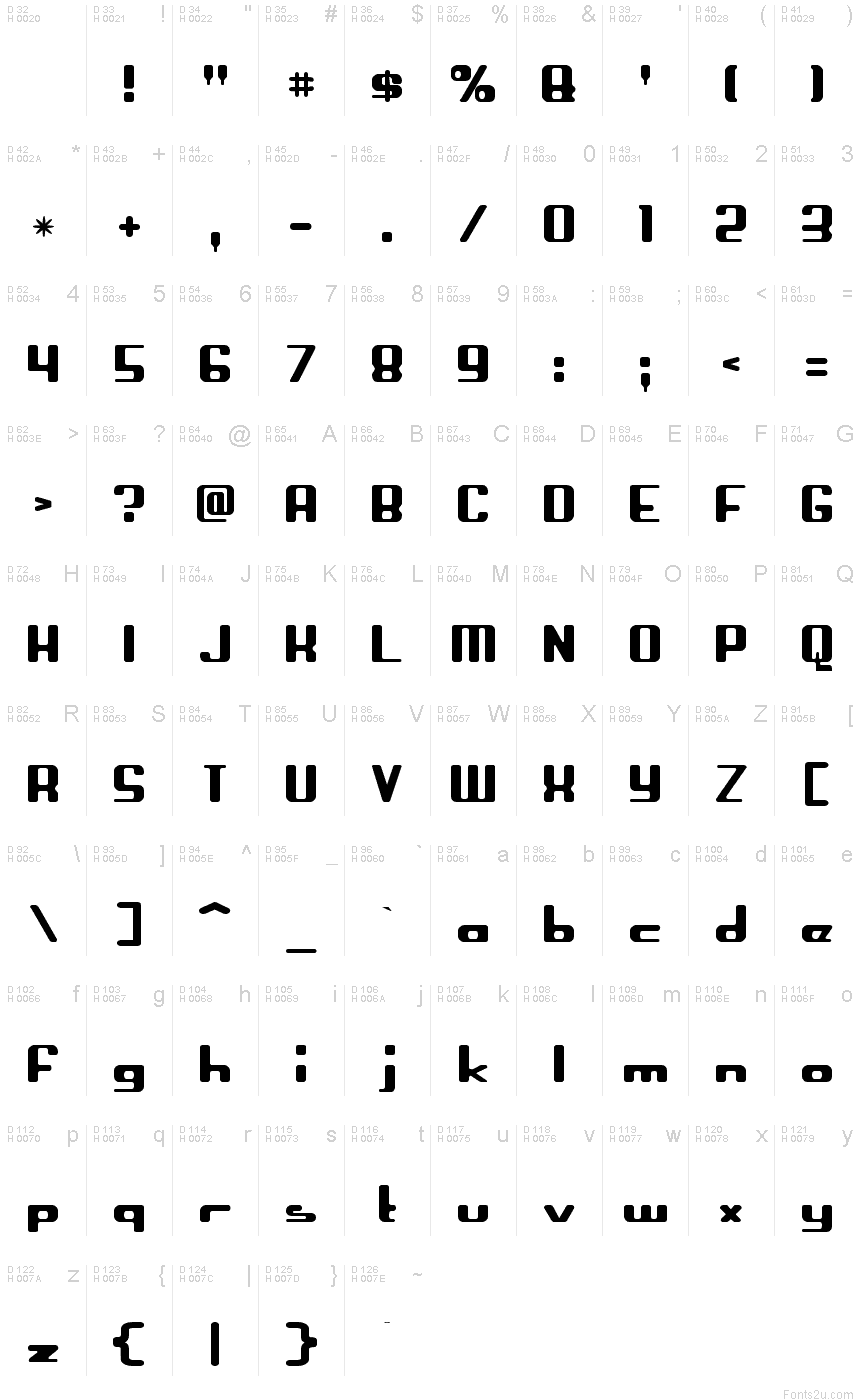
يُعد خط Crapola من تصميم Ray Larabie في Larabie Fonts خطًا تقنيًا (Techno) عريضًا ومستديرًا، يتميز بمنحنيات مربعة وخطوط انسيابية ذات سماكة موحدة. تمنح أشكاله الجريئة انطباعًا هندسيًا ولكن بلمسة مرحة، مما يضفي على العناوين طابعًا مستقبليًا طفيفًا دون أن يكون جامدًا. هذا الخط متاح مجانًا ويسهل دمجه في المشاريع التي تتطلب تأثيرًا قويًا بطابع ودود.
يعمل خط Crapola بشكل ممتاز في عناوين الألعاب، وعناوين الملصقات، وتصاميم الهوية البصرية لشركات التكنولوجيا أو الخيال العلمي، والرسومات الرياضية، وأغلفة الألبومات، وتصاميم التغليف الجريئة. يتألق هذا الخط المجاني عند استخدامه بأحجام كبيرة؛ لذا يُنصح بإقرانه بخط sans serif بسيط أو خط إنساني (humanist) للنصوص الأساسية للحفاظ على وضوح التخطيط وسهولة القراءة.